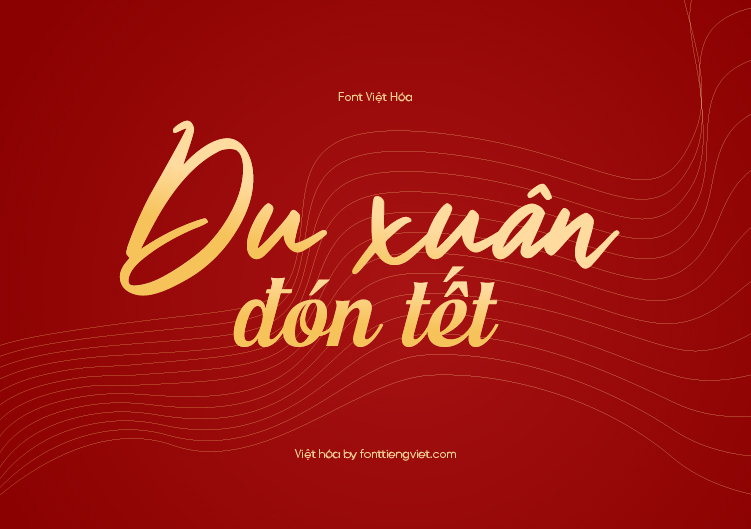
Font việt hóa 1FTV VIP Firegoods – Tết: Nét chữ rực rỡ cho mùa lễ hội truyền thống
Giới thiệu về Font việt hóa 1FTV VIP Firegoods – Tết
Trong không khí rộn ràng của những ngày cuối năm, việc tìm kiếm một bộ Font Chữ phù hợp để thiết kế thiệp chúc mừng hay băng rôn sự kiện là điều vô cùng quan trọng. Font việt hóa 1FTV VIP Firegoods – Tết nổi lên như một lựa chọn hàng đầu nhờ phong cách thiết kế độc đáo, kết hợp hài hòa giữa nét vẽ tay hiện đại và tinh thần lễ hội cổ truyền. Đây là bộ font được tối ưu hóa hoàn toàn cho bảng mã tiếng Việt, giúp người dùng dễ dàng sử dụng trong các phần mềm đồ họa chuyên nghiệp mà không lo lỗi hiển thị dấu câu.
Đặc điểm nổi bật của bộ font chữ
Bộ Font việt hóa 1FTV VIP Firegoods – Tết sở hữu những đường nét mạnh mẽ, uốn lượn mềm mại mô phỏng hình ảnh ngọn lửa ấm áp và sự thịnh vượng. Với cấu trúc ký tự rõ ràng, font chữ này không chỉ mang lại giá trị thẩm mỹ cao mà còn đảm bảo tính dễ đọc trên nhiều chất liệu in ấn khác nhau. Đối với các bạn học sinh và thầy cô giáo, đây là công cụ đắc lực để trang trí báo tường, thiết kế slide bài giảng chủ đề Tết Nguyên Đán hoặc làm thiệp tặng người thân.
Cách ứng dụng Font việt hóa 1FTV VIP Firegoods – Tết hiệu quả
Để phát huy tối đa vẻ đẹp của font, bạn nên kết hợp với các gam màu truyền thống như đỏ, vàng hoặc xanh lá cây. Font việt hóa 1FTV VIP Firegoods – Tết đặc biệt phù hợp cho các tiêu đề lớn, câu đối hoặc lời chúc ngắn gọn. Ngoài ra, việc sử dụng các hiệu ứng đổ bóng hay viền chữ sẽ giúp nội dung trở nên nổi bật và thu hút hơn trên nền background hoa mai, hoa đào.